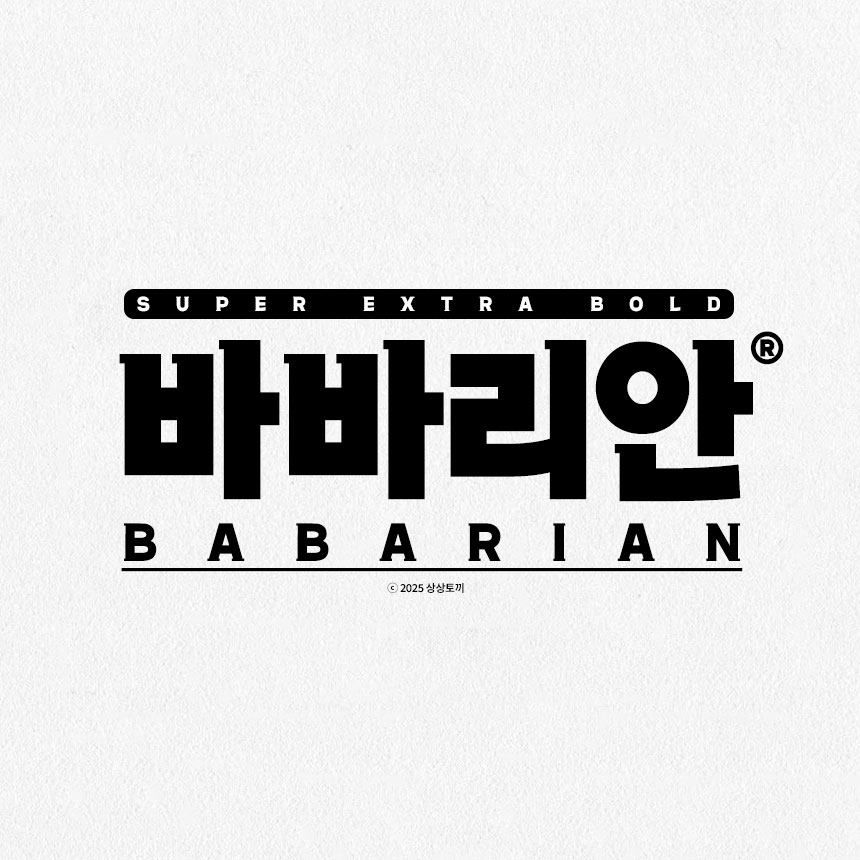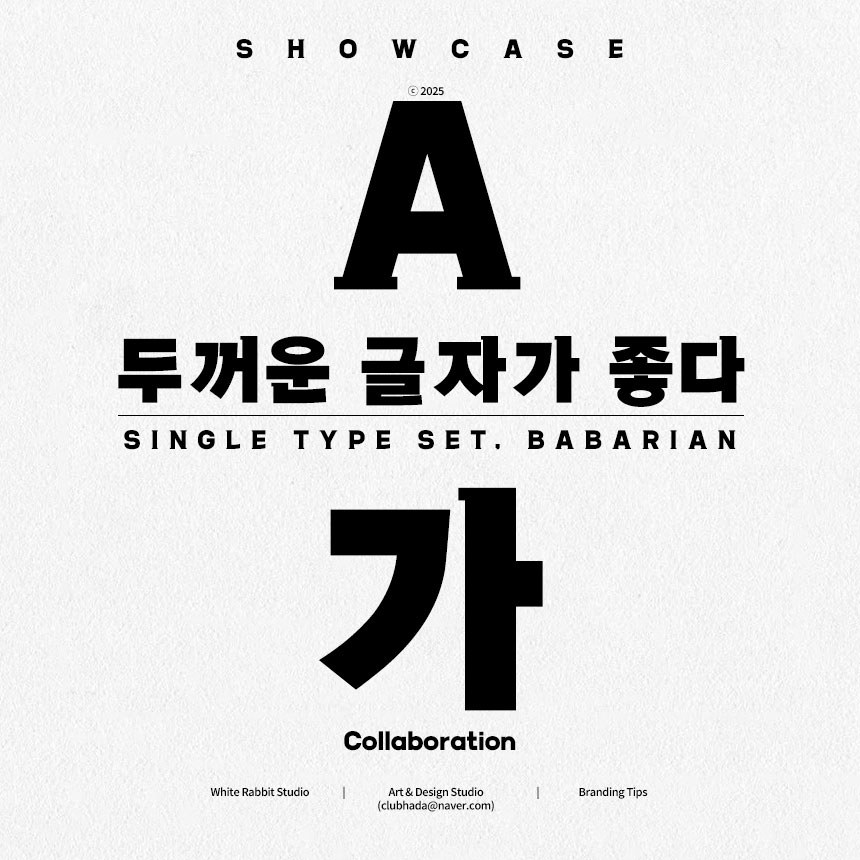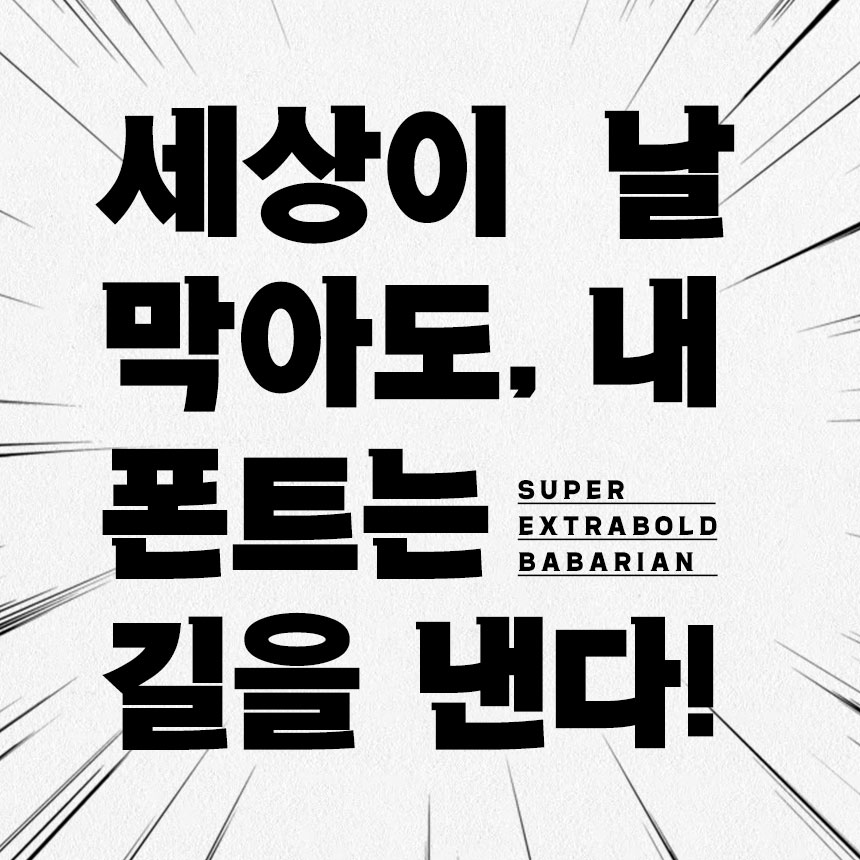
바바리안 레귤러
강한 인상의 엑스트라 볼드 타입 한글 폰트, 바바리안 레귤러
엑스트라 볼드 타입의 한글 폰트 <바바리안>을 제공합니다. 강한 인상이 필요한 타이틀에 적합한 폰트입니다.
바바리안(SUPER EXTRA BOLD)은 거친 힘과 강렬한 존재감을 강조한 제목용 서체입니다. 두꺼운 획과 각진 구조, 짧은 세로획 비율을 통해 묵직하고 남성적인 에너지를 표현하며, 브랜드 로고나 포스터, 헤드라인 디자인에 적합합니다. 특징 요약:
한마디로, 바바리안은 문장용이 아닌 힘을 전달하는 제목 전용 폰트입니다.